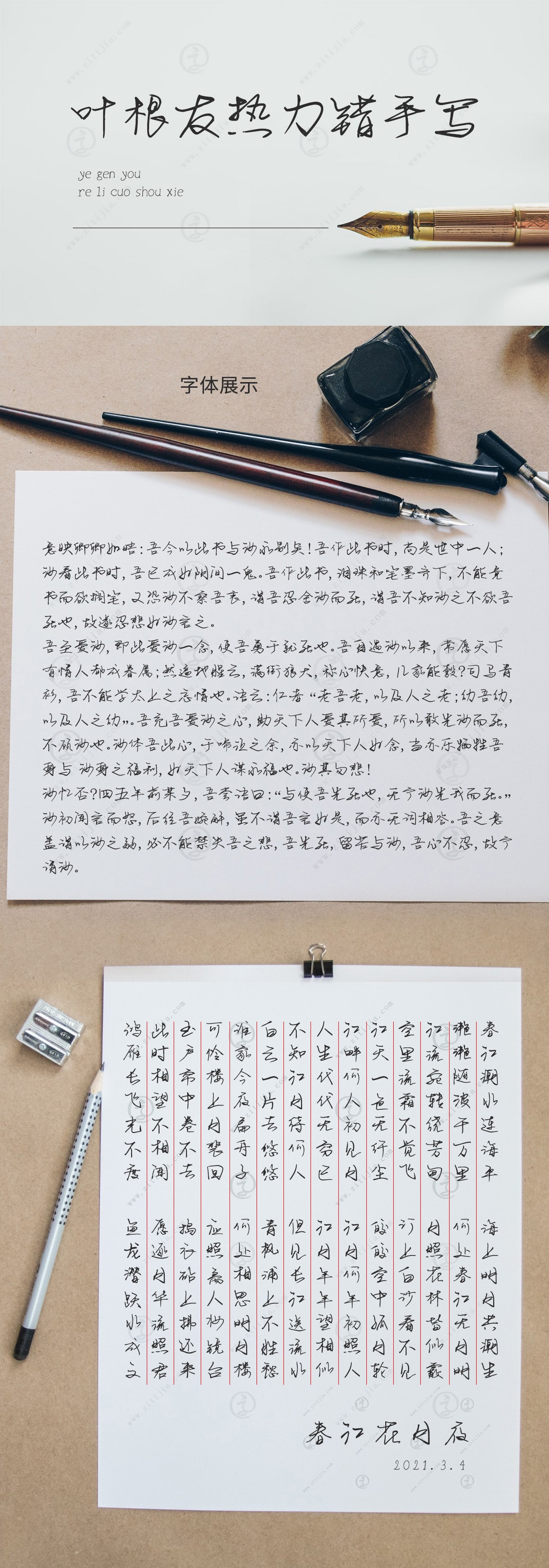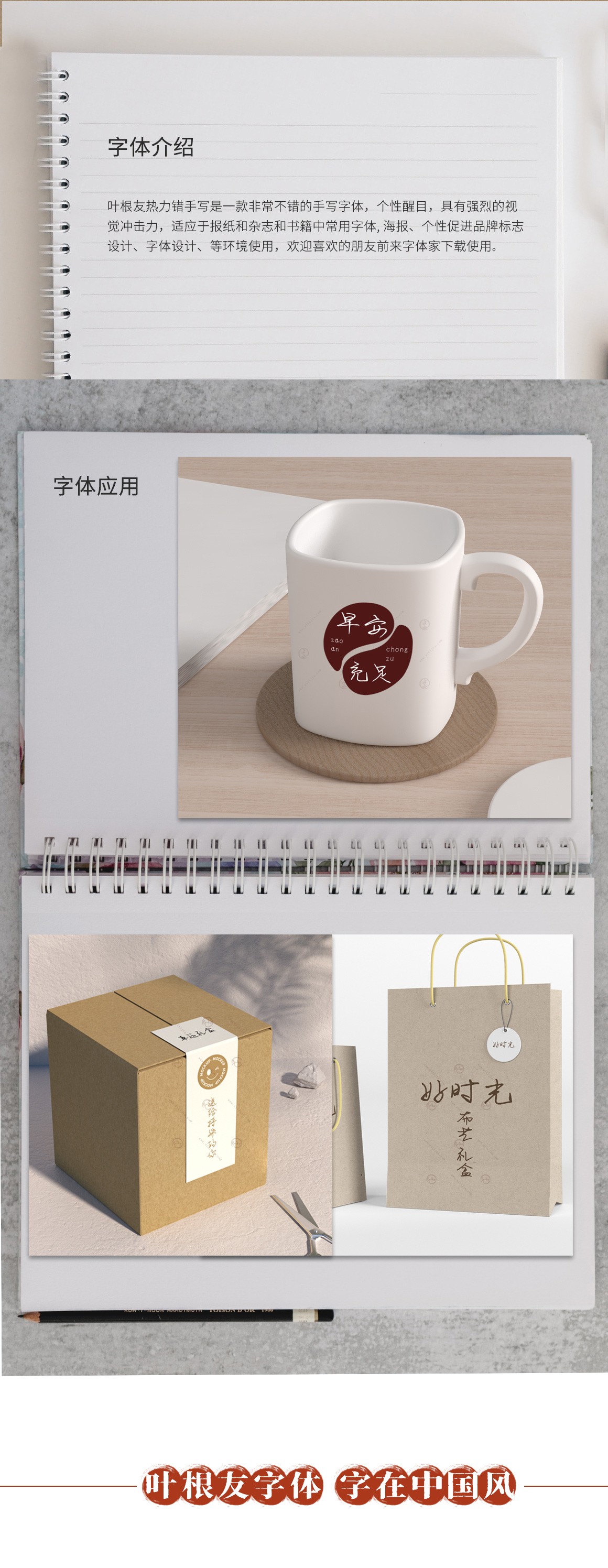
葉根友熱力錯(cuò)手寫是一款非常不錯(cuò)的手寫字體,個(gè)性醒目,具有強(qiáng)烈的視覺沖擊力,適應(yīng)于報(bào)紙和雜志和書籍中常用字體, 海報(bào)、個(gè)性促進(jìn)品牌標(biāo)志設(shè)計(jì)、字體設(shè)計(jì)、等環(huán)境使用。